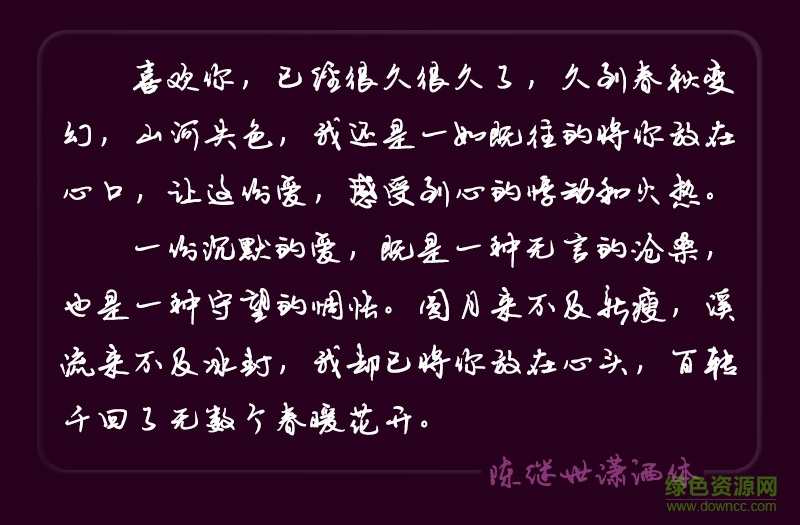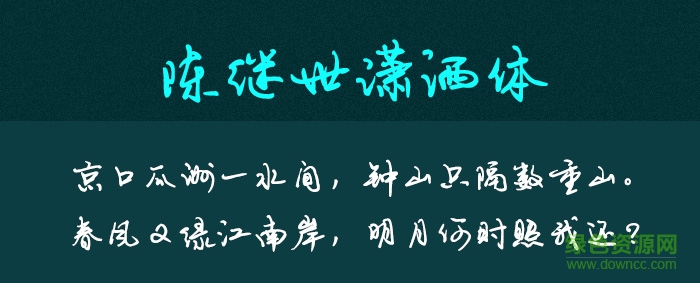
软件介绍 软件标签: 陈继世潇洒体 陈继世 字体 陈继世潇洒体是一款清新活泼的行书字体,让文字跳跃在书纸之间,更添美感和活泼之气,欢迎书法爱好者、艺术创作者、字体收藏者来绿色资源网下载使用!官方介绍陈继世潇洒体为中性笔书写的行书字体,字体书法韵味浓厚,潇洒流畅、舒展俊逸,为陈继世经典之作。可以作为字帖用字。字体安装方法一:直接将字体复制到C:\WINDOWS\Fonts。方法二:针对win7系统,用户只需选中字体右键安装即可。方法三:控制面板/字体/文件/安装新字体。商业授权请联系作者:陈继世 13944791389 qq:454282809 邮箱:qm666@163.com 软件截图 上一张下一张(1 / 1) 安装详细截图 猜你喜欢 陈继世字体 陈继世字体 陈继世字体是一种很不错的电脑字体,不仅字形美观,而且实用性强,可以用于很多方面,艺术设计、广告设计等都是很合适的,当然如果大家喜欢这些字体的话不管用在什么方面都是可以的,欢迎大家来绿色资源网下载。 查看更多>> 陈继世泰山体 1.48M/中文/10.0/下载 陈继世晓雯体 1.20M/中文/10.0/下载 陈继世行楷 1.88M/中文/10.0/下载 陈继世怪怪体常规 2.41M/中文/10.0/下载 陈继世古韵简体ppt字体 2.81M/中文/10.0/下载 陈继世潇洒体 1.78M/中文/10.0/下载 其他版本下载 标题 大小 更新日期 下载 下载地址 电脑版 陈继世潇洒体 点击报错 软件无法下载或下载后无法使用,请点击报错,谢谢! 关闭报错反馈 请描述您所遇到的错误,我们将尽快予以修正,谢谢! *必填项,请输入内容 本类最新 dreamweaver字体库 首尔南山体字体 v1.06 官方版 潮字社风云简ttf 潮字社凌渡鲲鹏简体字体 潮字社曾玉波手书简字体 微博慧心字体 相关文章 Photoshop字体安装使用方法和技巧 如何解决“无法新增字体”问题 Win 7系统安装字体方法 网页字体大小设置方法 怎么改网页字体大小 在Linux系统中安装字体的几种方法 windows7字体显示问题:打开某些程序的时候显示的是乱码 用户评论 热门评论 最新评论 发表评论 查看所有评论(0) 昵称: 请不要评论无意义或脏话,我们所有评论会有人工审核. 字数: 0/500 (您的评论需要经过审核才能显示)